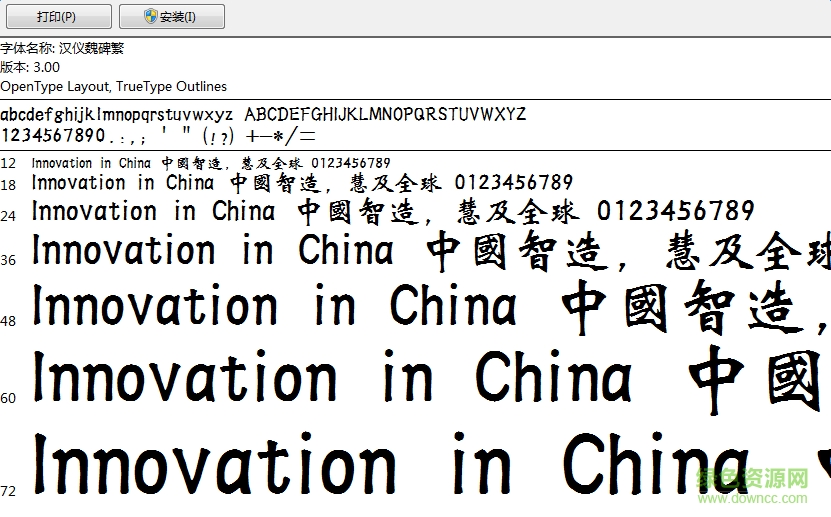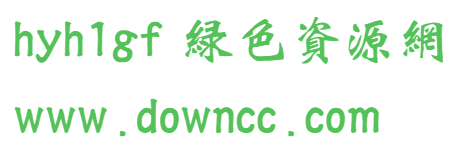
hyh1gf
hyh1gf字體(漢儀魏碑繁)是一款樸厚穩(wěn)重的繁體字體,魏碑字體也屬于楷書字體中一種,精美嚴(yán)謹(jǐn)有氣勢(shì),挺拔樸實(shí),適用于古籍排版、藝術(shù)設(shè)計(jì)等方面,歡迎下載!
魏碑字體特點(diǎn)
魏碑書法筆劃嚴(yán)謹(jǐn)、樸厚靈動(dòng),豐腴不失于板刻,上承漢隸,下開唐楷,兼有隸楷兩體之神韻。它的書法藝術(shù)是在漢隸和晉楷的基礎(chǔ)上發(fā)展演化而來(lái)的,堪稱漢碑中的上品。